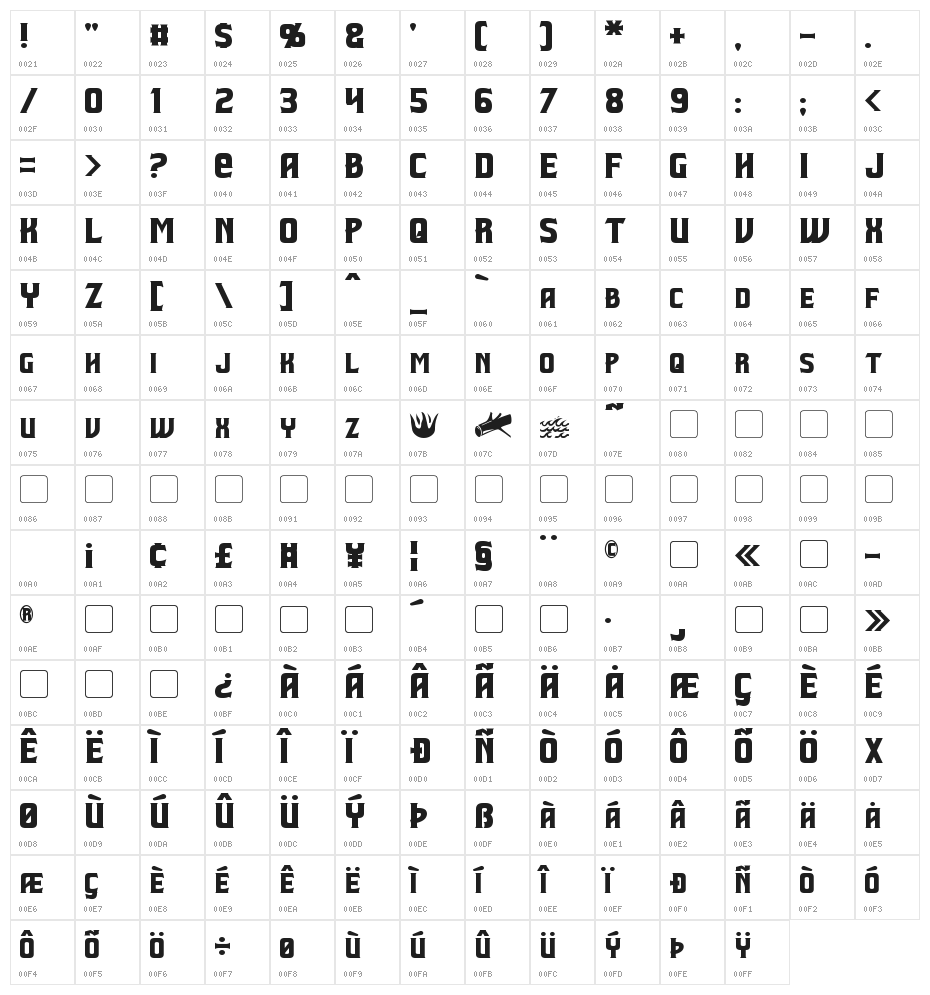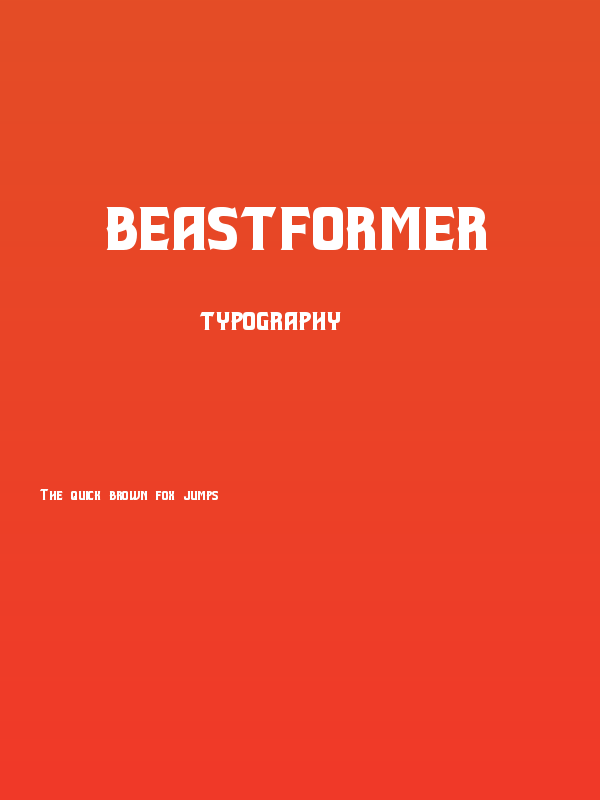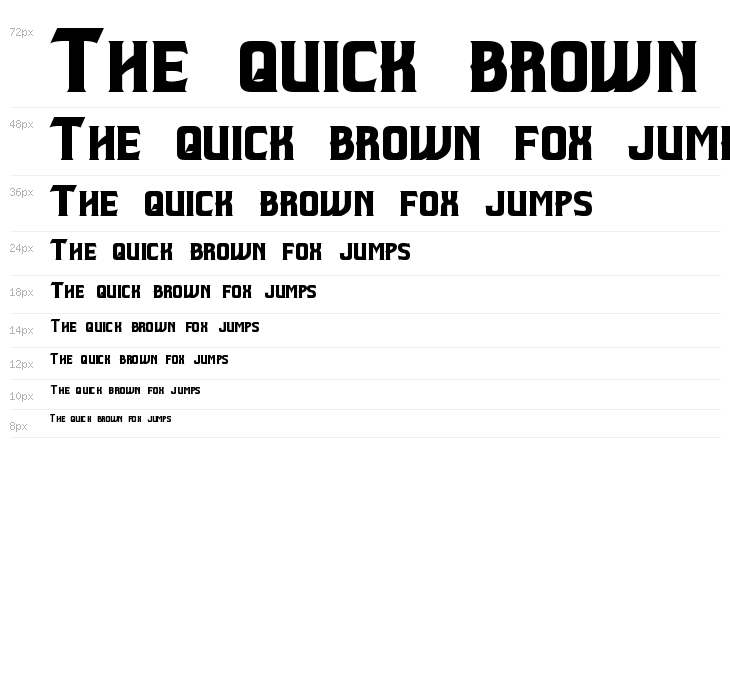
Beastformer Font
| Proyectos propuestos | Ideal for video game titles, movie posters, branding for tech companies, or any project needing a strong, impactful typeface. |